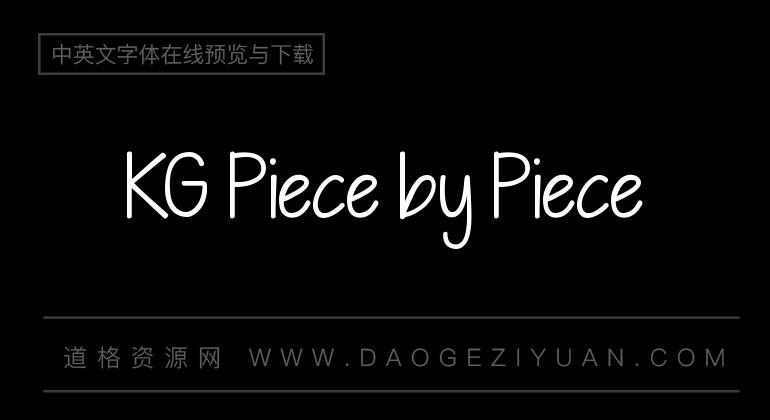
KG Piece by Piece是Kara Gordon(Kara Goucher)在2019年发布的一款字体。它是一款自由字体,可以用于商业用途,支持英文和拉丁文字母。KG Piece by Piece字体以手写字体为基础,形成了一种独特的视觉风格,既有传统的古典风格,又有现代的抽象风格。它可以用于制作标题、标签、海报、报纸和其他图形设计。内容介绍
KG Piece by Piece是一款非常不错的手写艺术字体,具有很好的视觉感,适合于文化类的宣传设计、商业类品牌的广告和产品包装设计以及个性化文字排版等较多场景。